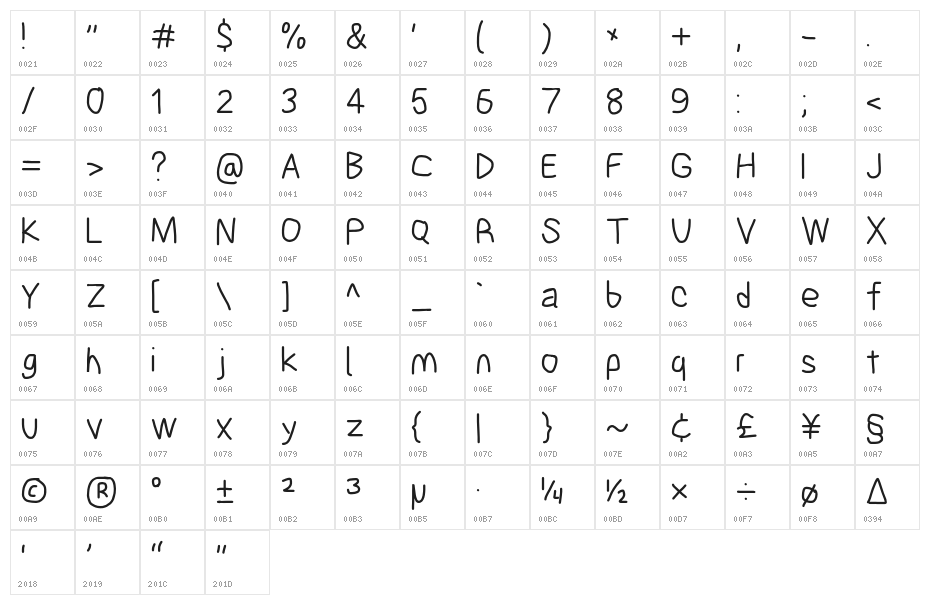
Blanket Font
| Gewicht | Poster |
| Gesamtstil | Casual, Playful |
| Anwendungsfall | Headlines, Informal text, Personal projects |
| Vorgeschlagene Projekte | Ideal for children's books, greeting cards, personal blogs, and informal branding projects. |